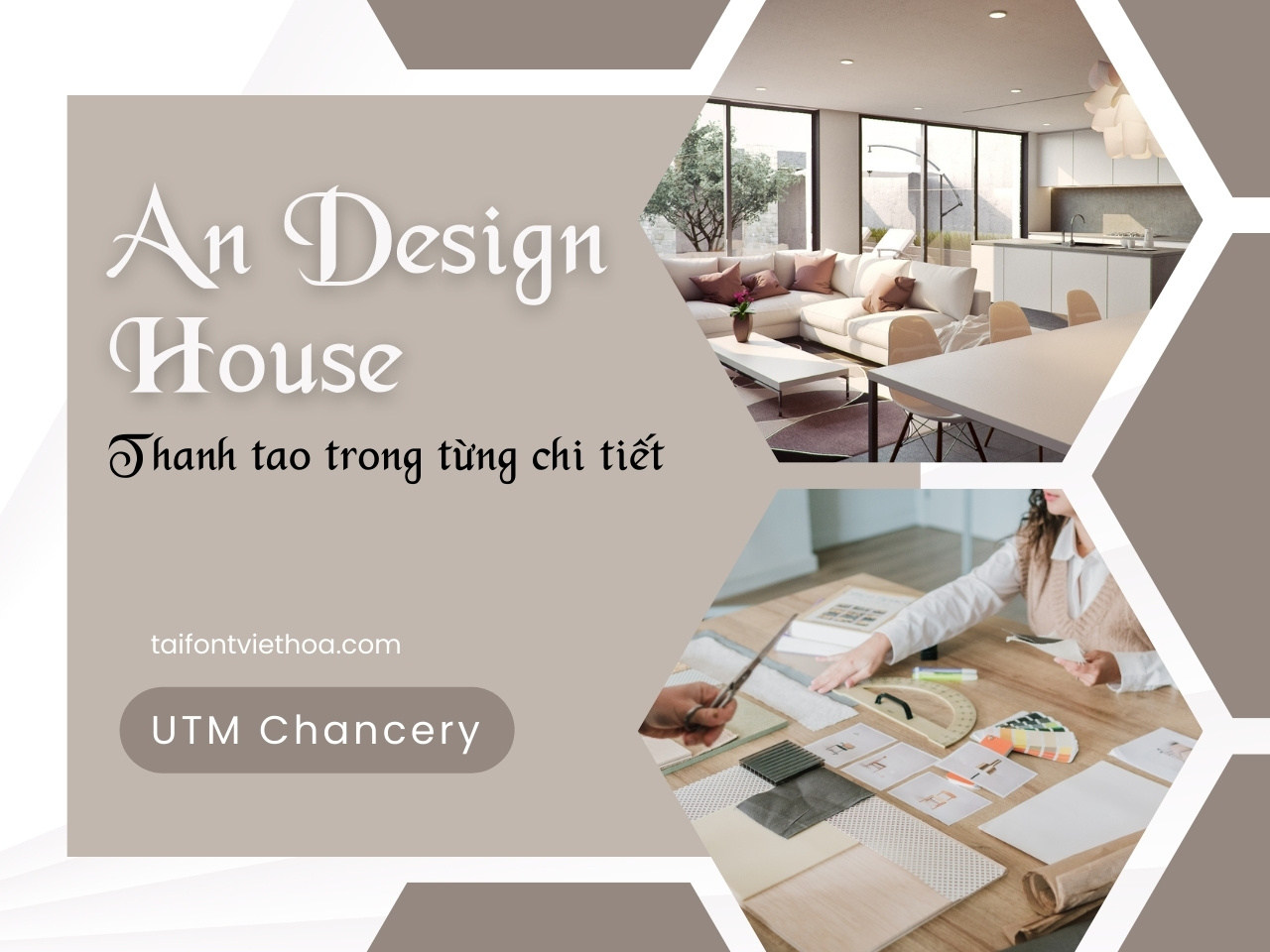
Giới thiệu về font UTM Chancery
UTM Chancery là phiên bản Việt hóa của font Chancery – một kiểu chữ script thanh lịch, có nguồn gốc từ phong cách chữ viết tay của thời kỳ Phục Hưng châu Âu. Font gốc nổi bật với các nét bút mềm mại, uyển chuyển và các đường cong tinh tế, mang lại vẻ đẹp cổ điển và sang trọng. Phiên bản Việt hóa đã được phát triển để hỗ trợ đầy đủ tiếng Việt cùng hơn 100 ngôn ngữ khác, giúp mở rộng khả năng sử dụng trong các dự án thiết kế nghệ thuật và trang trọng.
Font UTM Chancery được TFVH sưu tầm và lựa chọn kỹ càng nhằm phục vụ cộng đồng thiết kế Việt Nam. Phiên bản Việt hóa giữ nguyên tinh thần thanh lịch và tinh tế của bản gốc, đồng thời tối ưu khả năng hiển thị tiếng Việt, rất phù hợp cho các dự án thiệp cưới, branding và các ấn phẩm nghệ thuật cao cấp.
Đặc điểm thiết kế và ứng dụng của UTM Chancery
UTM Chancery sở hữu cấu trúc script với các nét bút thanh mảnh, liên kết mượt mà và các ligature đa dạng, giúp tăng tính linh hoạt trong thiết kế. Font có độ tương phản nhẹ nhàng, tạo cảm giác mềm mại, duyên dáng và lãng mạn, rất thích hợp cho các thiết kế mang phong cách cổ điển và nghệ thuật.
Font phù hợp sử dụng trong thiệp cưới, thiệp mời, thiết kế logo thương hiệu mỹ phẩm, poster nghệ thuật, bao bì sản phẩm thủ công và các dự án truyền thông cá nhân hóa cao. Các ngành nghề phù hợp gồm: tổ chức sự kiện, thời trang, làm đẹp, nghệ thuật sáng tạo, quảng cáo cá nhân hóa và thiết kế nội thất.